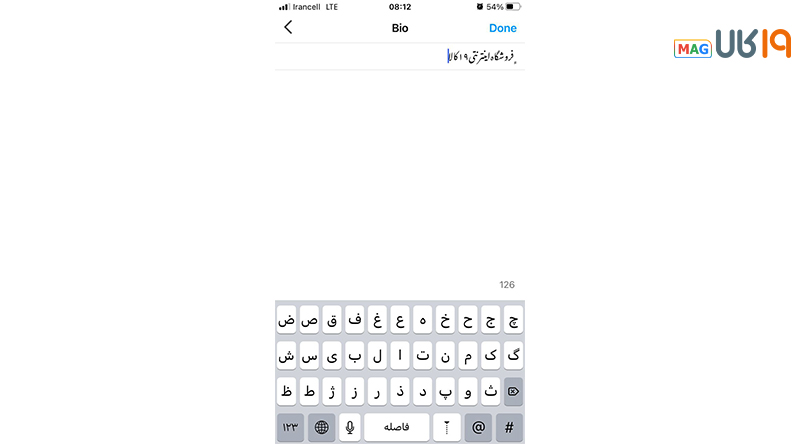
استفاده از فونت نستعلیق آنلاین برای اینستاگرام در اندروید و آیفون
شما هم فکر میکنید که استفاده از خط نستعلیق جلوهی متفاوت و ایرانیتری به استوری و پست میدهد؟ پس اگر به دنبال فونت نستعلیق آنلاین قابل کپی برای اینستاگرام هستید، در این مطلب همراه ما باشید تا یاد بگیرید چطور هم در بیو، هم کپشن و هم استوری، متن خود را بهصورت آنلاین یا با کمک یک کد ساده، به نستعلیق تبدیل کنید.
فونت نستعلیق آنلاین قابل کپی برای اینستاگرام (بیو و استوری)
نخستین خط ایرانی که پس از تعلیق شکل گرفت، نستعلیق بود که یکی از نمونههای مهم هنر ایرانی محسوب میشود و میتوان گفت به نوعی ریشه در فرهنگ ما دارد. اینستاگرام هم فضاییست که در آن متن و تصویر کنار هم دیده میشوند و طبیعی است که خیلیها دوست داشته باشند برای نمایش شعر، دیالوگ یا بیو، از خط نستعلیق آنلاین قابل کپی استفاده کنند.
اینجا باید به یک نکتهی مهم اشاره کنیم: اینستاگرام بهصورت پیشفرض فونت نستعلیق ندارد و هیچ روشی وجود ندارد که مثل ویندوز، یکبار فونت را نصب کنید و همهجا فعال شود. کاربرانی که بهدنبال «فونت نستعلیق آنلاین برای بیو» یا «تبدیل فونت فارسی به نستعلیق آنلاین قابل کپی» هستند، در عمل دو انتخاب دارند:
- استفاده از سایتها و اپلیکیشنهایی که متن را با نستعلیق روی تصویر رندر میکنند (برای استوری و پست عالی است، ولی متن دیگر قابل ویرایش نیست).
- استفاده از کد و علامت مخصوص نستعلیق (مثل ﮼) که باعث میشود بخشی از متن در بیو یا استوری، روی خود گوشی با فرم نستعلیق نمایش داده شود.
در ادامه، هم ابزارهای نستعلیق آنلاین را معرفی میکنیم و هم روش استفاده از کد نستعلیق در اندروید و آیفون را بهطور کامل توضیح میدهیم تا بتوانید بسته به نیاز خود، بهترین روش را انتخاب کنید.
فونت نستعلیق آنلاین و تبدیل متن فارسی به نستعلیق
اگر به دنبال سایتی هستید که در زمینه فونت نستعلیق آنلاین امکانات ارائه دهد، انتخابهای محدودی دارید. با این حال، ما سعی کردیم تا در این بخش بهترین سایتها را به شما معرفی کنیم.
Canva به عنوان فونت نستعلیق آنلاین برای اینستاگرام
اپلیکیشن Canva یکی از آن مواردی است که در هر زمینهای حتی درست کردن لوگوی جذاب به کاربران خود کمک میکند. این اپلیکیشن نسخه وب هم دارد و شما میتوانید از طریق سایت Canva وارد شوید و پروژههای جدید خود را در قالب استوری اینستاگرام درست کنید.
البته باید این نکته را بدانید که شما باید فونت نستعلیق را به صورت جداگانه دانلود و اضافه کنید. برای اضافه کردن فونت نستعلیق آنلاین برای اینستاگرام میتوانید از راهنمایی کوتاه زیر کمک بگیرید:
فونت آنلاین نستعلیق در سایتی سادهتر
اگر به دنبال سایت سادهتری هستید که تنها با چند کلیک ساده عکس خود را ادیت کنید، این مورد مناسب شماست. نستعلیق آنلاین در حال حاضر بهترین ابزار فونت آنلاین نستعلیق است که بدون نیاز به ثبت نام و به سادگی در همهی پلتفورمها قابل دسترس است.
این وبسایت به شما اجازه میدهد متن دلخواهتان را با فونت نستعلیق بنویسد، آن را سفارشی کنید و در صورت تمایل یک قاب تذهیب برای آن انتخاب کرده و در نهایت آن را به صورت یک فایل jpg و یا png ذخیره کنید. میتوانید نتیجه را به صورت پست و یا استوری در اینستاگرامتان به اشتراک بگذارید.
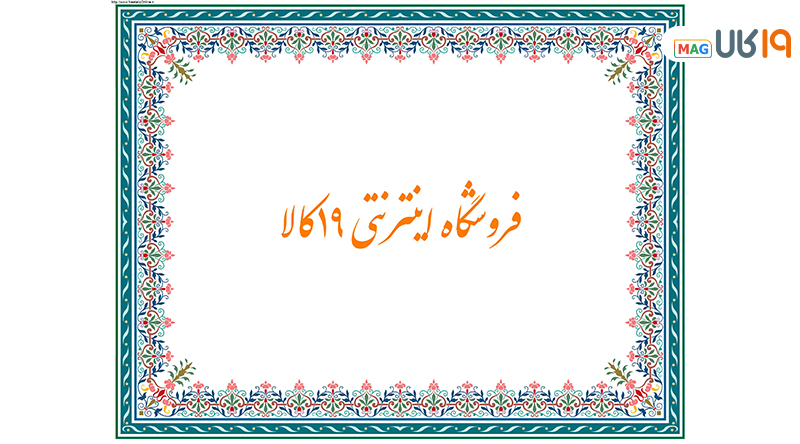
اردو آنلاین
وبسایت دیگری که نوشتن به وسیلهی فونت نستعلیق اینستاگرام یا هر استفادهی دیگری را در اختیار شما قرار میدهد، اردو آنلاین است.
همان طور که نام این وبسایت پیداست، زبان مورد استفاده در آن فارسی نیست، ولی با توجه به شباهتهای میان دو زبان اردو و فارسی در نوشتن، میتوانید از «اردو آنلاین» برای ساخت عکسنوشتههای نستعلیق استفاده کنید.
همان طور که واضح است این ابزارهای آنلاین محدودیتهای بسیاری دارند و عملاً بهترست به جای این ابزار فونت نستعلیق در اینستاگرام از برنامهها و یا ترفندهای دیگری که قابلاجرا هستند استفاد کنید. در ادامه همهی روشهای استفاده از این فونت در اندروید و آیاواس را بررسی میکنیم…
فونت نستعلیق برای اندروید با کیبورد
اندروید یک سیستمعامل منبعباز است که امکانات و قابلیتهای بسیاری برای شخصیسازی در اختیار کاربرانش میگذارد. در اندروید حتی اگر بخواهید میتوانید یک اینستاگرام جداگانه داشته باشید که فونت کلی آن نستعلیق باشد. برای این کار باید فایل ttf فونت «ایران نستعلیق» را دانلود کنید، آن را در مکان مشخصی از حافظهی گوشیتان ذخیره کنید، سپس به وسیلهی برنامهای مانند “app cloner” یک نسخهی جدید از اینستاگرام بسازید. عملاً با این فونت نستعلیق برای اندروید اینستاگرام خود را به شکل دیگری طراحی کنید.
با این حال در این مقاله هدف و تمرکز ما بیشتر بر نوشتن با خط نستعلیق در اینستاگرام برای ساخت پست و استوری و یا حتی طراحی یک بیو جذابتر بوده و از همین رو بیش از این به تغییر فونت کلی این برنامه نمیپردازیم. در ادامه روشهای استفاده از کیبورد نستعلیق برای اینستاگرام را بررسی میکنیم.
کیبورد انگلیسی اردو – اردو
این اپلیکیشن یکی از بهترین کیبوردهای زبان اردوست که امکان استفاده از فونت نستعلیق در اینستاگرام را نیز در اختیار شما قرار میدهد.
طراحی با خط نستعلیق در اینستاگرام با اپلیکیشن
اگر هم بخواهید از نستعلیق در اینستاگرام برای طراحی پست و یا استوری استفاده کنید، برنامههایی در دسترس هستند که به شما اجازه ادیت عکسهایتان و ساختن هر سبک عکس نوشتهای که بخواهید را میدهند. در ادامه چند عنوان از این برنامهها را معرفی میکنیم.
علامت « ﮼ » را قبل از هر کلمه ای که میخوای وارد کن تبدیل به فونت نستعلیق میشه
برای تبدیل متن به نستعلیق من InShot رو پیشنهاد میدم کار کردن باهاش راحته